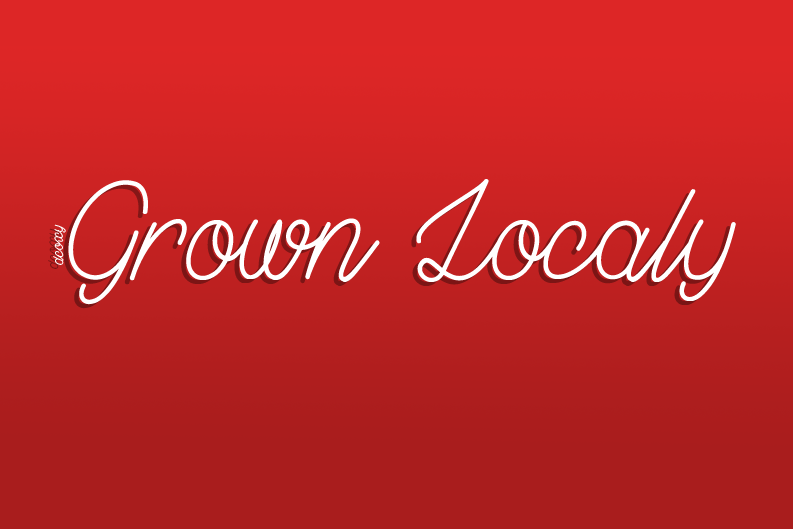
A fonte Grown Localy é uma escolha perfeita para quem busca um charme único e autêntico em sua próxima projeto. Desenvolvida por Greg Medina, essa fonte handwritten traz um toque de delicadeza e personalidade que não pode ser encontrada em outras. Se você está procurando por algo mais profundo e envolvente para suas criações, Grown Localy é a escolha certa. Grown Localy é perfeitamente adequada para aplicações onde o escritório adquire um toque de autenticidade e humanização, como anúncios de marketing local ou elementos gráficos para websites. Com seu estilo natural, essa fonte consegue capturar a essência do conteúdo ao qual está sendo aplicado. Para qualquer cliente que esteja considerando usar esta fonte em suas criações comerciais ou promocionais, é essencial contactar o designer antes:  Com Grown Localy na sua paleta de ferramentas, você pode trazer uma sensação mais pessoal e autêntica às suas composições. Esta é a fonte perfeita para qualquer projeto que valoriza a verdadeira essência da comunicação visual.